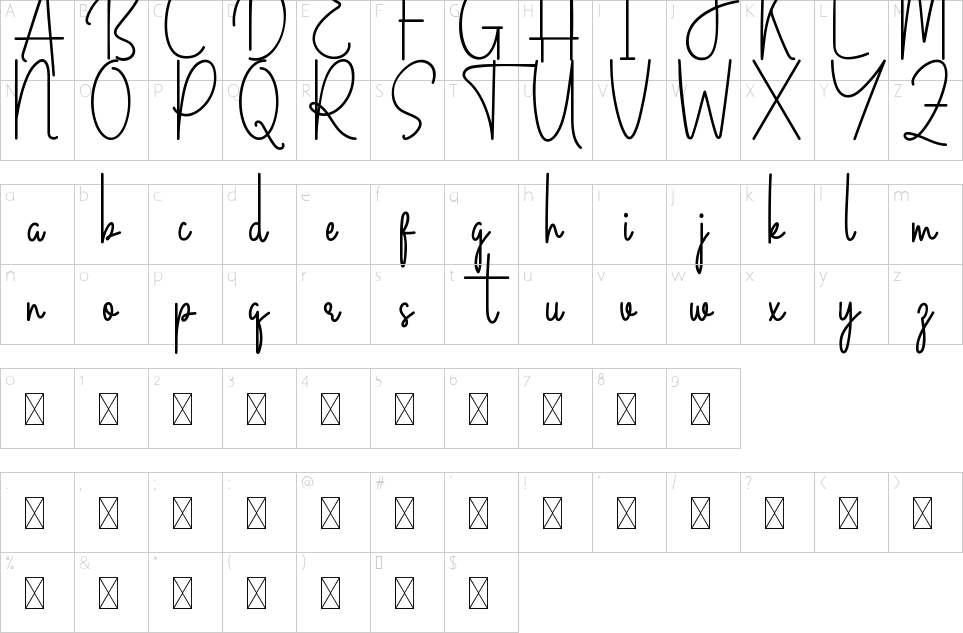
Aulion é uma fonte elegante e sofisticada que oferece um toque moderno ao seu design. Desenvolvida por CalligraphyFonts, esta fonte é um excelente recurso para designers e fãs do estilo que buscam uma combinação perfeita de elegância e praticidade. Com uma aparência arredondada e detalhes atraentes, Aulion combina com diversos estilos de design, desde elegantes gráficos de newsletter até ambientes de escritório profissional. Se você está procurando por uma fonte moderna que não se encaixa na linha de fontes tradicionais, Aulion pode ser o que você estava procurando. Sua fácil adesão aos outros tipos de letra e suas variedades de negrito e itálico tornam Aulion uma ótima escolha para quem busca uma fonte versátil. Aulion foi baixada 2.806 vezes, demonstrando seu valor entre os criadores de materiais digitais.